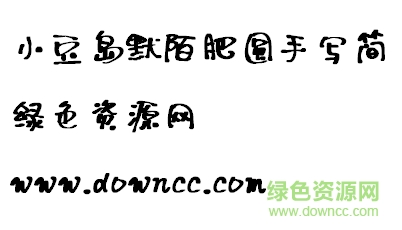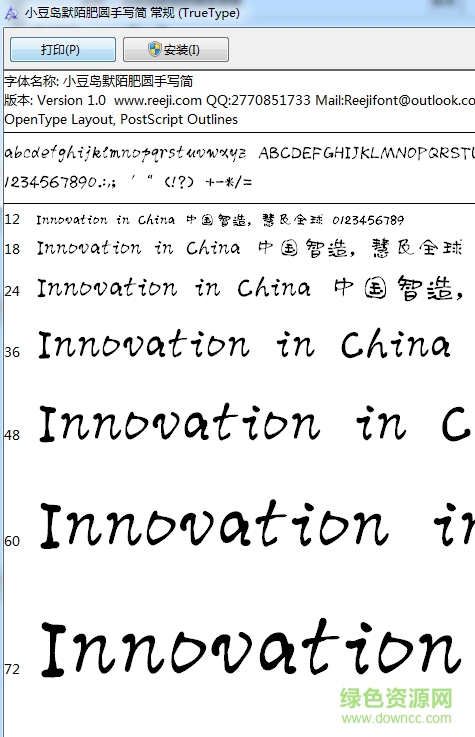
小豆島默陌肥圓手寫簡
小豆島默陌肥圓手寫簡是一款令人賞心悅目的手寫字體,字體粗細相間,形如流水,整體有著無拘無束的韻味,更多好看的字體歡迎到綠色資源網(wǎng)下載!
小豆島默陌肥圓手寫簡字體家族系列主要提供常規(guī)等字體風格樣式,該字體尾部的甩尾有力且有豐富的筆觸細節(jié),大字效果突出且引人注目;并且最大程度還原作者書寫字形,細節(jié)表現(xiàn)完整,且字庫完整,可以廣泛應用于名片設計、新聞媒體、宣傳海報、ppt、影視制作以及內(nèi)容用字等領域。
小豆島默陌肥圓手寫簡字體是類似于草書的手寫藝術字體,打造不同尋常的特色書法,讓你的平面設計與眾不同,每一個字體都有不一樣的藝術魅力!